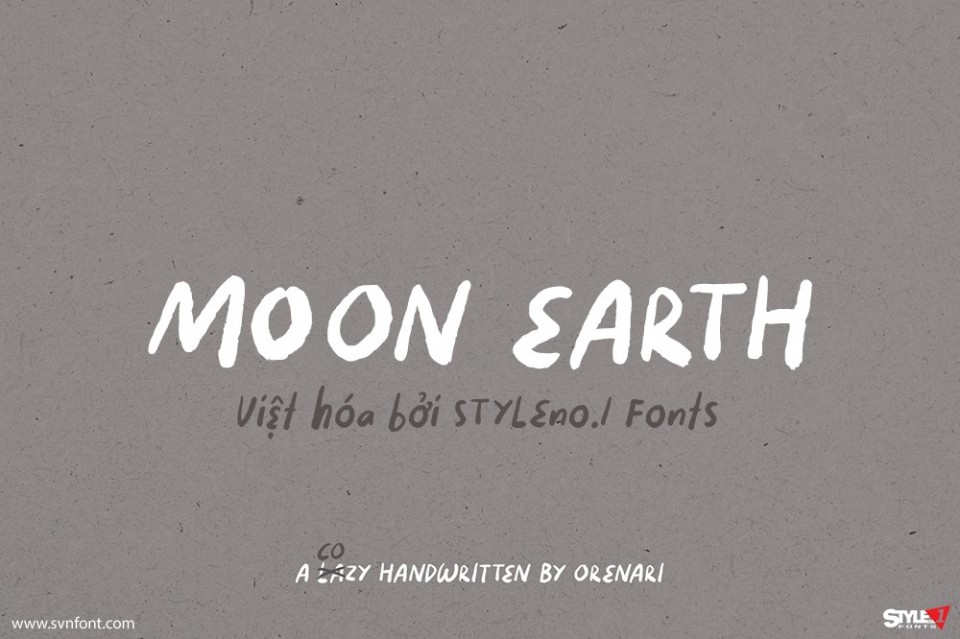
Font việt hóa SVN Moon Earth
Font việt hóa SVN Moon Earth – Lựa chọn hoàn hảo cho thiết kế giáo dục sáng tạo
Giới thiệu về Font việt hóa SVN Moon Earth
Trong thế giới thiết kế đồ họa dành cho học sinh và nhà trường, việc tìm kiếm một bộ Font Miễn Phí có phong cách vừa gần gũi vừa hiện đại là điều vô cùng quan trọng. Font việt hóa SVN Moon Earth chính là giải pháp lý tưởng giúp các thầy cô và các bạn học sinh tạo nên những bài giảng hay báo tường sinh động. Với đường nét tròn trịa và bố cục hài hòa, bộ font này mang lại cảm giác dễ chịu, giúp người xem dễ dàng tiếp nhận thông tin một cách tự nhiên nhất. Đây là một trong những phông chữ tiêu biểu giúp truyền tải thông điệp về sự khám phá và học hỏi không ngừng.
Đặc điểm nổi bật của Font việt hóa SVN Moon Earth
Thiết kế thân thiện và dễ đọc
Đặc trưng của Font việt hóa SVN Moon Earth nằm ở các nét vẽ đều đặn, không quá cứng nhắc nhưng vẫn giữ được sự chuyên nghiệp. Điều này cực kỳ phù hợp với các tài liệu giảng dạy hoặc các dự án sáng tạo của học sinh. Sự kết hợp giữa nét chữ thanh thoát và tính ứng dụng cao giúp phông chữ này trở nên linh hoạt trong nhiều hoàn cảnh khác nhau.
Khả năng tương thích và Việt hóa chuẩn xác
Bộ font này đã được tối ưu hóa hoàn toàn cho tiếng Việt với đầy đủ các dấu câu cần thiết, không xảy ra lỗi hiển thị khi đánh máy. Người dùng có thể yên tâm sử dụng trong các phần mềm văn phòng cơ bản như Word, PowerPoint hay các công cụ thiết kế chuyên sâu hơn. Điều này giúp tiết kiệm thời gian chỉnh sửa và đảm bảo tính thẩm mỹ đồng nhất cho toàn bộ văn bản.
Ứng dụng Font việt hóa SVN Moon Earth trong học tập